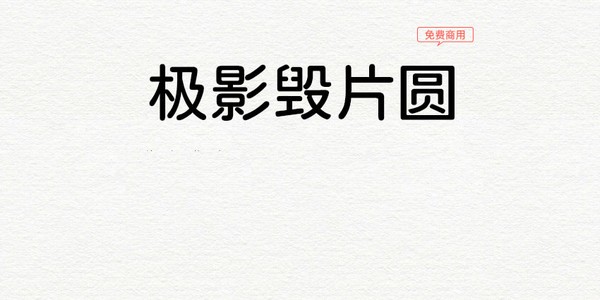
極影毀片圓全新的免費(fèi)中文字體,獨(dú)特的線(xiàn)條以及優(yōu)美的圓體加上剛勁有力的比劃帶來(lái)全新的字體效果,適合各種給不同的場(chǎng)合以及要求滿(mǎn)足各種人群所需帶來(lái)諸多的方便,安裝簡(jiǎn)單實(shí)用性高值得一試。需要的朋友趕緊來(lái)下載吧!
極影毀片圓是一款以小衫圓體、江城圓體、獅尾圓體等混合而成的字體,補(bǔ)全了Unic ode的中日韓統(tǒng)一表意文字,并且根據(jù)通用規(guī)范漢字表,修正常用的簡(jiǎn)體字的筆畫(huà)所整理而成!
極影毀片圓是以小衫圓體、思源黑體所修改而成的字體。
本字體以jf open粉圓為底本,使用江城圓體3.0、獅尾圓體SC作為增補(bǔ),補(bǔ)全了Unic ode的中日韓統(tǒng)一表意文字,并且根據(jù)通用規(guī)范漢字表,修正常用的簡(jiǎn)體字的筆畫(huà)所整理而成的字體。本字體支持簡(jiǎn)體中文、繁體中文、日語(yǔ)的正常顯示。
我整理本字體的初衷,是很多媒體視頻的字幕制作,都在選擇圓體作為主字幕正文。隨著B(niǎo)站UP主等自媒體的逐漸興趣,我覺(jué)得能夠有一個(gè)適合的視頻字幕正文顯示的字體,使大家更方便地“毀片”是一件很好的事情。
因?yàn)橹饕紤]是使用字體在字幕顯示,所以本字體暫時(shí)僅有Medium(500W)這一種字重。
由于思源黑體和jf open粉圓的設(shè)計(jì)區(qū)別,而且本人能力有限,很多字都是手動(dòng)調(diào)整的,所以該字體不可避免地在筆畫(huà)、粗細(xì)、大小、位置等出現(xiàn)一些不一致的情況。接下來(lái)我會(huì)在使用的過(guò)程中逐漸更新本字體,使本字體更加完善。